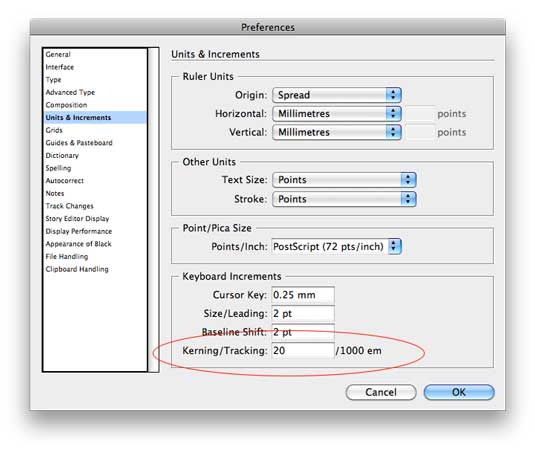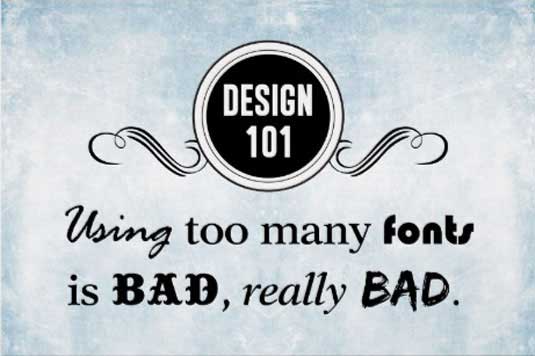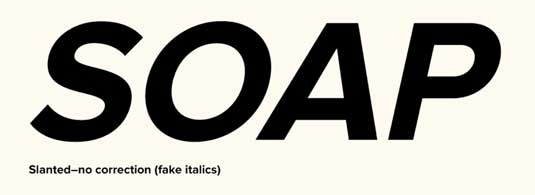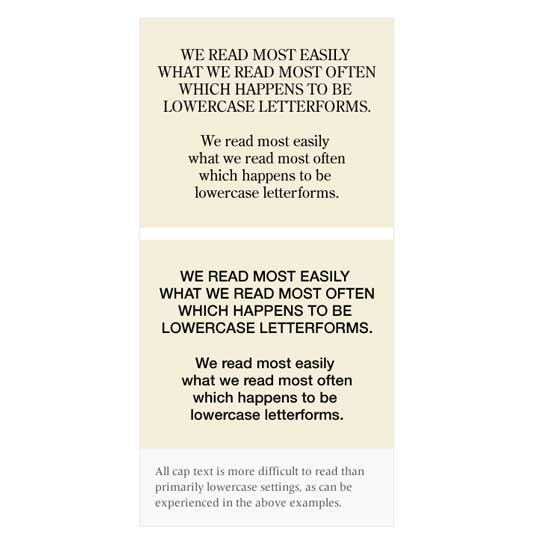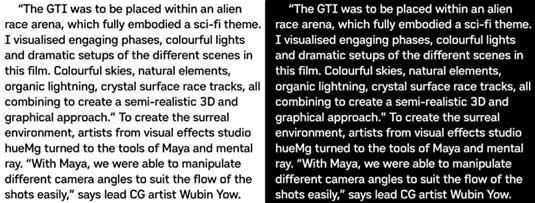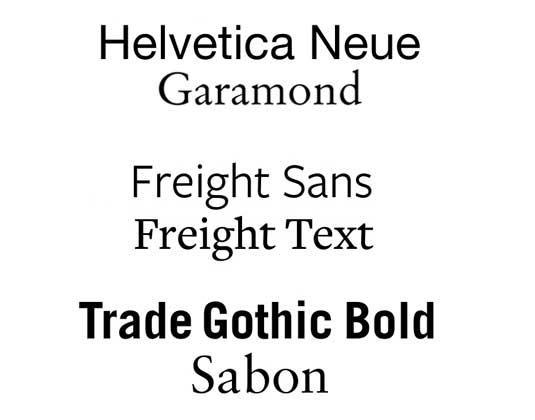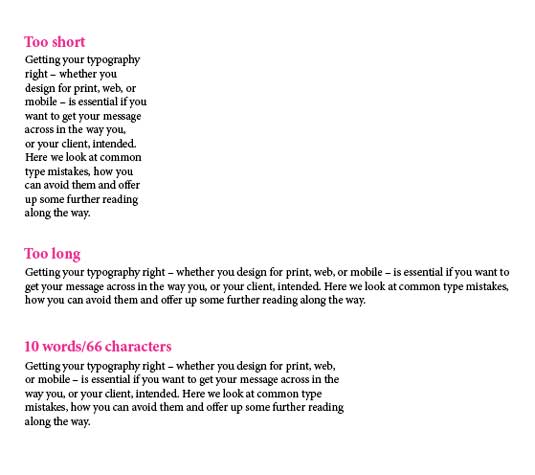
Páginas web: Los diez mandamientos de la tipografía
¿Has estado cometiendo estos pecados tipográficos en tus páginas web? En este artículo Staff Digital y Creative Bloq han juntado los crímenes más atroces en contra de la tipografía y cómo evitarlos.
Ya sea que diseñes para páginas web o móviles, escoger una tipografía correcta es esencial si deseas hacer que el mensaje llegue de la forma en que tú o tu cliente desea.
Veamos los errores de tipografía más comunes y cómo corregirlos.
1. No usarás interletrado por defecto
Vemos este error con bastante frecuencia: un gran diseño web arruinado por un interletrado de mala calidad. Al configurar cualquier encabezado en InDesign, Illustrator o, incluso, Photoshop, no confíes en el “razonamiento” de un software.
Tómate un tiempo para mirar el espaciado entre los pares de letras (interletrado) y el espaciado de las palabras completas (tracking). Tienes mucho control sobre el interletrado y tracking en InDesign.
En primer lugar, ve a Preferencias > Unidades e Incrementos > Incrementos de teclado > Interletrado/Tracking y configura el incremento que necesitas. Ahora, puedes usar las teclas Alt/Opt e Izquierda/Derecha para ajustar tu espaciado.
2. No usarás las fuentes script con exageración
Las fuentes script, o escritas, no añaden “clase” automáticamente a un diseño web. Su uso necesita ser considerado con cuidado.
Sí, existen momentos cuando una fuente script funciona (usualmente en grandes tamaños, tal vez en un diseño de logo vintage o algo similar), pero para los proyectos generales de páginas web, son algo innecesario.
Piensa en cuántas veces has visto esta fuente Zapfino apareciendo de la nada en encabezado e, incluso, cuerpos de texto en carteles poco profesionales, volantes y otros materiales impresos. Sí, es feo, y definitivamente no deberías incluso pensar en una fuente script en ninguna clase de texto. Simplemente no lo hagas, nadie lo leerá.
3. No colocarás tipografía sobre fondos cargados
No existe algo peor que no ser capaz de leer un mensaje porque el fondo es más fuerte que él. Sí, puedes tener una imagen hermosa que necesiten ir en el fondo de tu página web, pero no busques espacio para colocar tu texto: piensa en el tratamiento de texto de una forma sutil.
Tal vez necesites configurar tus fuentes en bloques de colores sólidos para hacer que resalten, o incluso cortar la imagen de una forma diferente y colocar tu texto en cualquier otro lugar del diseño. Piensa en la legibilidad. Tal vez tú seas capaz de leerlo (tú sabes lo que dice), pero tu audiencia puede pasarlo desapercibido.
4. No usarás varias fuentes
Este es el pecado capital de la tipografía, usar demasiadas fuentes. Sí, lo hemos mencionado antes, pero es tan importante que sentimos que debemos volver a hacerlo.
Aunque todos tenemos acceso a miles de fuentes gratis de buena calidad para usar en nuestros proyectos de diseño web gracias a Google Fonts y otros servicios como Font Squirrel, no necesitas usarlas todas al mismo tiempo.
Usar varias fuentes en una página web, revista o en cualquier pieza de diseño puede confundir y distraer a tus usuario del mensaje que deseas transmitirles. Una regla general es no usar más de tres fuentes en tu diseño web (aunque existen excepciones).
5. No crearás mayúsculas falsas
Crear, o falsificar, mayúsculas pequeñas jamás se ve bien; de hecho, lucen categóricamente horribles. Así que si estás buscando añadir un poco de variación a tus encabezados al usar mayúsculas pequeñas, escoge una fuente que cuente con una. Existen cientos de fuentes de buena calidad disponibles, solo mira estos ejemplos para que te des una idea.
6. No usarás cursivas falsas
Aunque es bastante raro encontrar una fuente sin una versión en cursiva, si estás usando una, no te tienes a distorsionarla para hacerla lucir cursiva… No va a lucir bien. Después de todo, tus curvas estarán distorsionadas, el peso visual estará desincronizado y todo será un desastre.
7. No usarás solo mayúsculas
Aunque las mayúsculas se pueden ver mucho más profesionales, no atrevimos a decir, en cuerpos de texto, usar mayúsculas en todas las palabras convertirá tu importante mensaje en un caos ilegible.
¿La razón? Bueno, la razón más común es que no leemos letra por letra, sino por formas de palabras que son, en parte, creadas por la posición de aumento y descenso de los caracteres. Así que si creas algo solo con mayúsculas, será todo un reto para tu usuarios.
8. No usarás fuentes en colores invertidos
Al igual que el mandamiento siete, invertir el color de las fuentes para contrastar con un color obscuro no logra nada para la legibilidad. Debes evitar una textos blanco sobre un fondo blanco cuando presentas un párrafo para hacerlo fácil de leer. Forzar a los usuarios a concentrarse en el texto blanco por un tiempo largo puede causar estrés en la vista de los usuarios.
Y el décimo primer mandamiento…
No usarás Comic Sans.
Teníamos que mencionarlo.